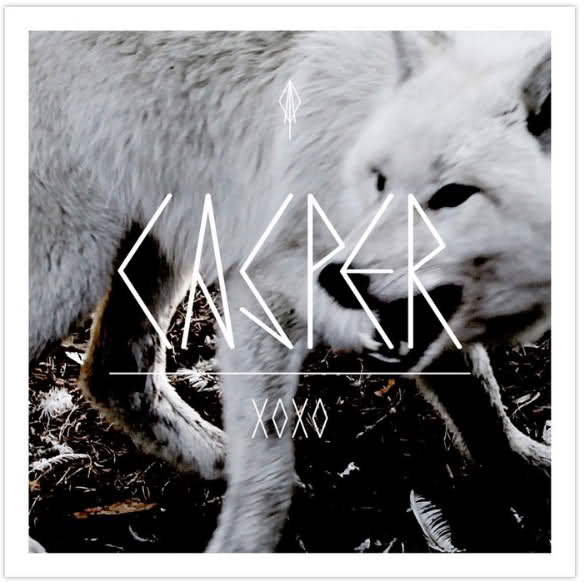
Welche Schriftart ist das ? [CD-Cover]
Es gibt schon so einiges in der Richtung, was angeblich Schrift sein soll … die Herkunft dürfte ja bekannt sein. Da würde es mich nicht wundern, wenn auch dieser Kasperl einem Font entsprang.